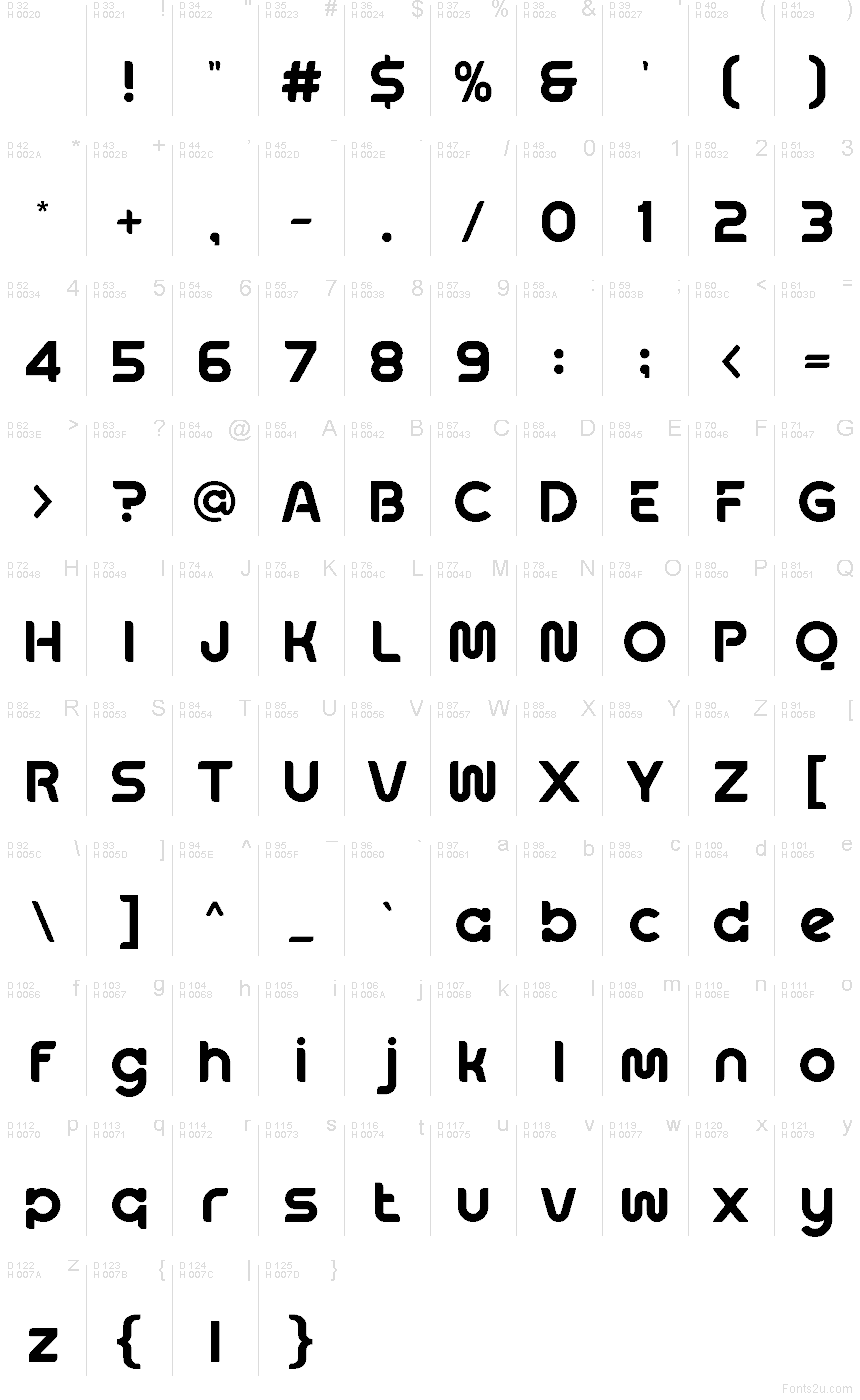
Mequin, da Ermedia Studio, é uma fonte display moderna e gratuita, com letras largas e arredondadas e uma silhueta nitidamente futurista. Os seus traços grossos alternam entre arcos suaves e cortes retos abruptos, enquanto junções abertas e espaços internos compactos conferem ao desenho uma estrutura personalizada, semelhante a um logótipo.
O design de embalagens é um suporte especialmente adequado para as suas formas limpas, mas nada convencionais, sobretudo em produtos de tecnologia, streetwear ou cosméticos. A fonte também se adapta muito bem a cartazes de música e artes gráficas digitais. Em todas essas aplicações, a combinação de curvas suaves e quebras de perfil técnico aproxima o design de produtos contemporâneo da estética dos clubes e da música eletrónica.